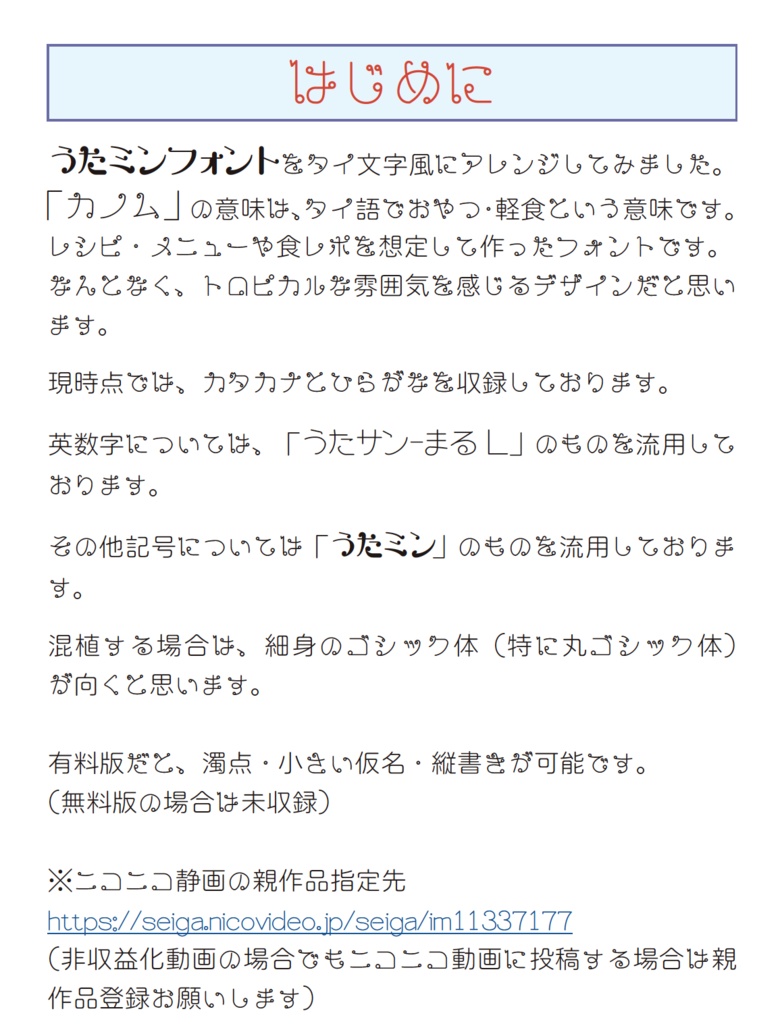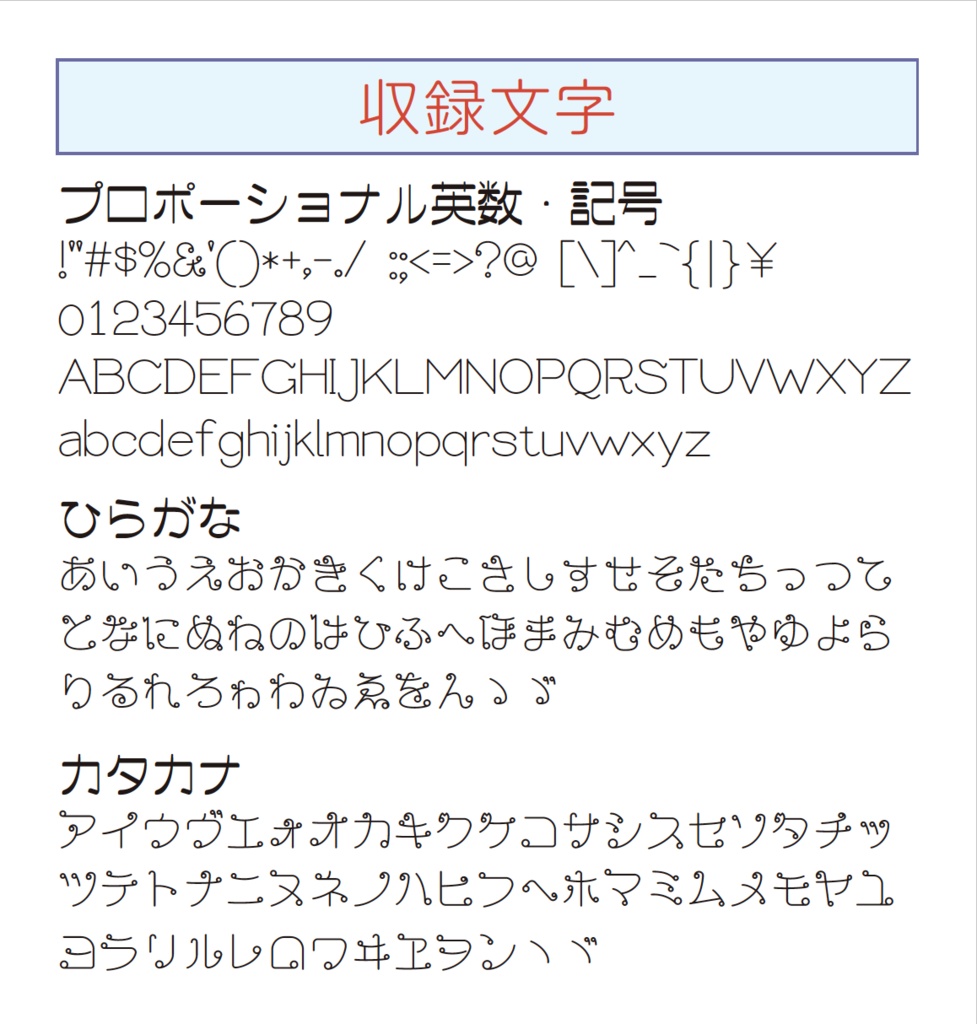
カノム 無料版(うたミンフォントタイ文字風アレンジ)
うたミンシリーズのセット版の販売スタートしました。 ↓ 記事: https://palettype.fanbox.cc/posts/9541140 セット版: https://palettype.booth.pm/items/2884800 ============================================== うたミンフォントをタイ文字風にアレンジしてみました。 「カノム」の意味は、タイ語でおやつ・軽食という意味です。 レシピ・メニューや食レポを想定して作ったフォントです。 なんとなく、トロピカルな雰囲気を感じるデザインだと思います。 現時点では、カタカナとひらがなを収録しております。 英数字については、「うたサン-まる L」のものを流用しております。 その他記号については「うたミン」のものを流用しております。 混植する場合は、細身のゴシック体(特に丸ゴシック体)が向くと思います。 有料版だと、濁点・小さい仮名・縦書きが可能です。 (無料版の場合は未収録) ※ニコニコ静画の親作品指定先 https://seiga.nicovideo.jp/seiga/im11337177 (非収益化動画の場合でもニコニコ動画に投稿する場合は親作品登録お願いします) 有料版 https://palettype.booth.pm/items/5359916